以前、チラシを作るときの「レイアウトのコツ」をまとめた記事をご紹介しましたが、今回はフォントについてご紹介します。
なぜフォントが重要なのかというと、印刷物の内容を相手に伝えるためには、読みやすくイメージが伝わりやすい「見出し」や「本文」でデザインする必要があります。
例えば、お年寄りから子どもまで参加する賑やかで楽しいフリーマーケットのチラシの見出しに使うフォントであれば、「細身の明朝体」よりも「やや太めのゴシック体」や「ポップな印象のデザイン書体」の方がイベントのイメージに合いそうです。
もちろん全体のデザインやコンセプトにもよりますので、明朝体がNGというわけではありませんが、伝えたい内容に合わせて適切なフォントを選ぶというのは重要であることに間違いありません。
今回はフォントの入手先と、チラシ・フライヤーで使えるオススメのフォントについてご紹介いたします。
フォントの入手先
フォントには大きく3つの入手先があります。
標準フォント
一つ目はあらかじめパソコンに入っているフォントです。もともとインストールされているものなので入手というよりは既に用意されているものですね。
チラシなどに使うフォントであれば、windowsなら「メイリオ」「遊ゴシック」は読みやすく洗練された印象で、とても使いやすいフォントです。Macであればなんといっても有名なのは「ヒラギノ」フォントです。文字としての読みやすさはもとより、太さが10段階もあり非常に使い勝手の良いフォントです。ゴシック体と明朝体それぞれ用意されています。
無料フォント
二つ目の入手先は、無料フォントです。フォントメーカーや個人のフォントクリエイターが配布しているフォントで、パソコンにインストールして使うことができます。中にはとてもユニークで他では見られないフォントも存在します。
有料フォント
チラシ・フライヤーにオススメのフォント
さて、それではチラシ・フライヤーに使用するオススメのフォントをご紹介します。今回は「見出し」に使えるオススメフォントをピックアップしました。
見出しは一番最初に目に入ってくる情報です。そのために、もっともフォントにこだわりをもつべき部分と言っても過言ではありません。フォントは大きく分けると「明朝体」「ゴシック体」「デザイン書体」に分けることができます。伝えたいイメージに近いフォントを選ぶと、印象が格段にアップします。
信頼感のある真面目な印象の「明朝体」
法律事務所や病院など、知的で信頼感のある印象を出すには明朝体がオススメです。ヒラギノ書体でも十分に雰囲気を出すことができます。映画「天気の子」などでも使われている、墨だまりの美しいA1明朝も大変オススメです。
ヒラギノ明朝 Std W3
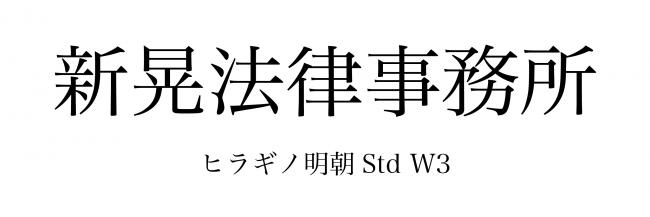
A-OTF A1明朝 Std Bold
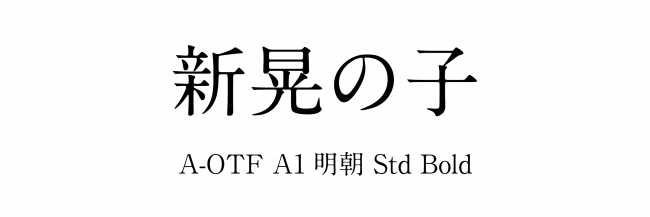
読みやすくレイアウトしやすい「ゴシック体」
線に強弱のある明朝体に比べ、比較的均一な線で構成されているのがゴシック体です。そのため視認性がよく、見出しや強調したい部分に使われることも多く、扱いやすいフォントと言えます。あらかじめパソコンに入っているメイリオ、ヒラギノなども使いやすいですが、A-OTF 見出ゴMB301などはその名の通り、見出しにはぴったりの堂々とした作りのフォントです。
ヒラギノ角ゴ Std W6
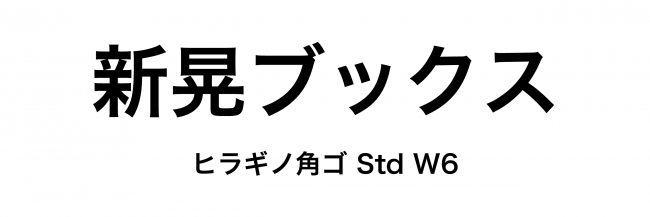
A-OTF 見出ゴMB301 ProMB31
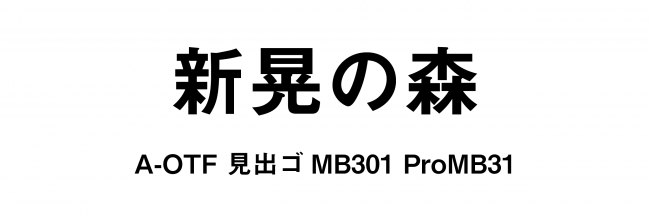
遊び心満載な「デザイン書体」
フォントが持つキャラクター性とも言えるデザイン書体。表現したいイメージにばっちりハマったフォントを選ぶと、クオリティが格段にアップします。ポップで軽やかな印象のキリギリス、アニメ「鬼滅の刃」などで使われている闘龍、など見ているだけでも楽しいですね。ぜひ参考にしてみてください。
TA-キリギリス
A_KSO 闘龍
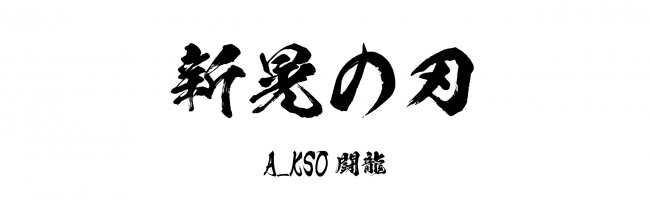
いかがでしたでしょうか。ちなみに「本文」は見出しに近い雰囲気のフォントを選ぶとまとまりやすくなります。ただし、デザイン書体は多用すると読みにくい場合がありますので、明朝体かゴシック体のどちらかにすると読みやすい上に、見出しと本文のメリハリがついたデザインになります。ぜひ試してみてください。